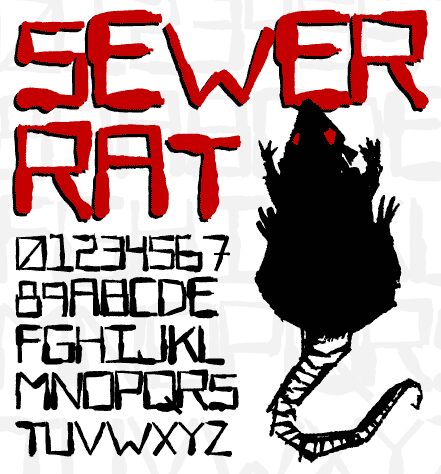
Sewer Rat von Ominous Cat Art & Design ist eine kostenlose Horror-Display-Schrift, die wie verschmierte, an die Wand gekratzte Pinselstriche wirkt. Die Buchstaben sind unruhig und schmutzig, mit stumpfen, ungleichmäßigen Strichen, wackeligen Kanten und einem lockeren, handgemachten Rhythmus, der das Schriftbild roh und ungeschönt lässt.
Sie ist ideal für Punk-Poster, Horror-Zines, Underground-Filmtitel, Skate-Grafiken oder Halloween-Flyer, wo eine Schrift mit so viel „Dreck“ und Dynamik sofort für sich spricht. Nutzen Sie sie für kurze Überschriften, Cover-Lines oder raue Monogramme, wenn die Schrift instabil und wild wirken soll.